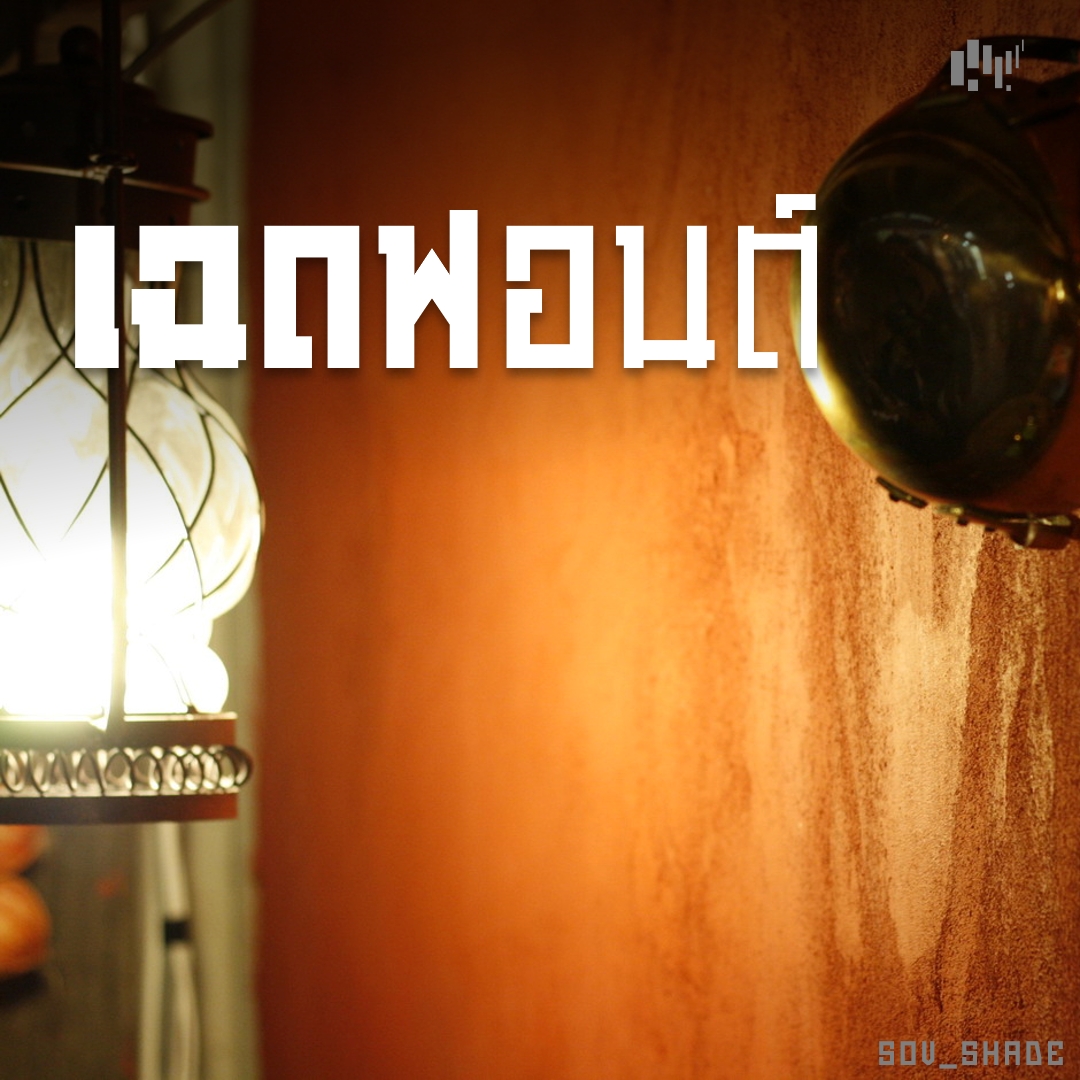
ฟอนต์ เฉด
ฟอนต์เฉด เป็นฟอนต์เดียว ประกอบด้วย 10 น้ำหนัก ไล่น้ำหนักอัตโนมัติเวลาพิมพ์
ชื่อฟอนต์ : เฉด
ใจร้ายอีกแล้วครับ ทำมาให้ใช้ตั้ง 10 น้ำหนัก แต่รวมทุกน้ำหนักไว้ในฟอนต์เดียว 555555 ชื่นชมแนวคิดนอกกรอบมาก ๆ ครับอา